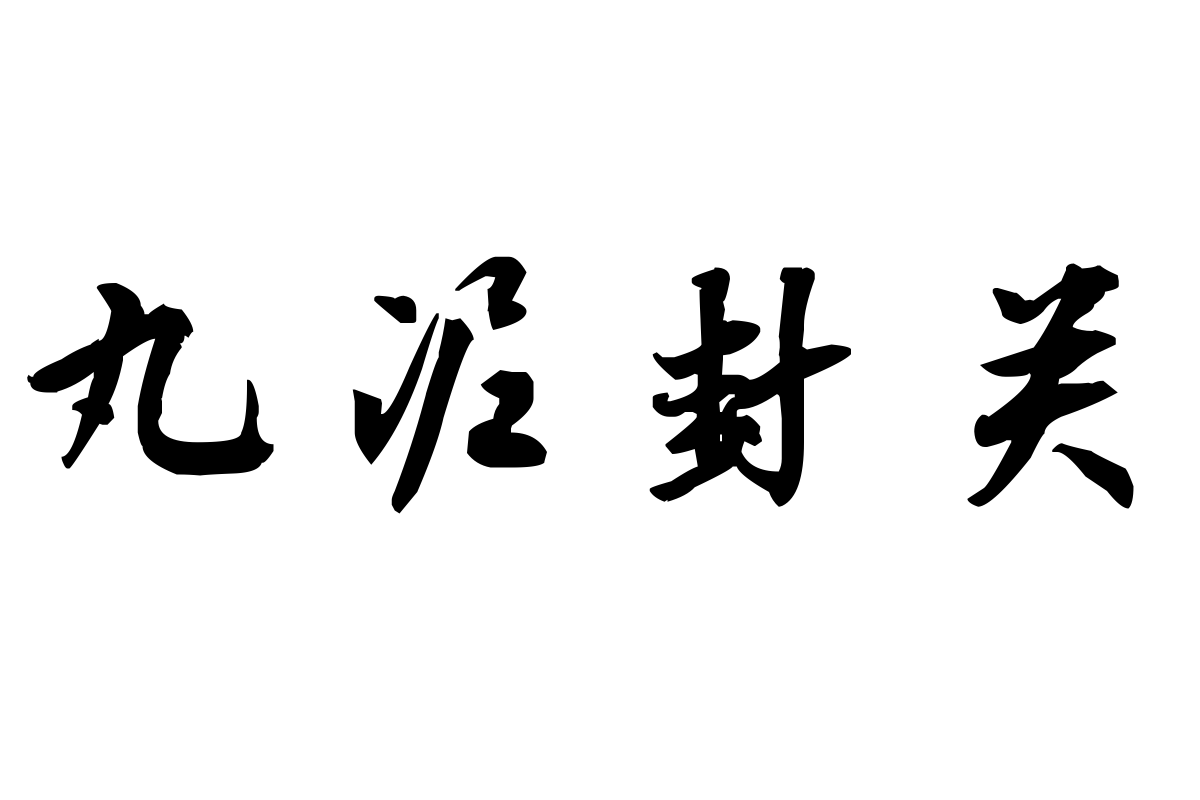
汉呈王世李行书字体是一种特殊的书法风格,它融合了古代汉字的书写技巧和现代审美观念。这种字体以其独特的线条和结构,展现了一种既传统又现代的审美观。
汉呈王世李行书字体的特点如下:
1. 线条流畅:汉呈王世李行书字体的线条非常流畅,给人一种优雅的感觉。这种流畅的线条使得整个字体看起来更加和谐,更具美感。
2. 结构紧凑:这种字体的结构非常紧凑,每个字都紧密相连,没有多余的空间。这使得整个字体看起来更加整洁,更具现代感。
3. 笔画变化丰富:汉呈王世李行书字体的笔画变化非常丰富,既有直线又有曲线,既有粗线又有细线。这种丰富的笔画变化使得整个字体看起来更加生动,更具艺术感。
4. 笔触有力:这种字体的笔触非常有力,每一个笔画都充满了力度,给人一种强烈的视觉冲击。
总的来说,汉呈王世李行书字体是一种非常独特且具有现代感的书法风格,它融合了古代汉字的书写技巧和现代审美观念,展现了一种既传统又现代的审美观。